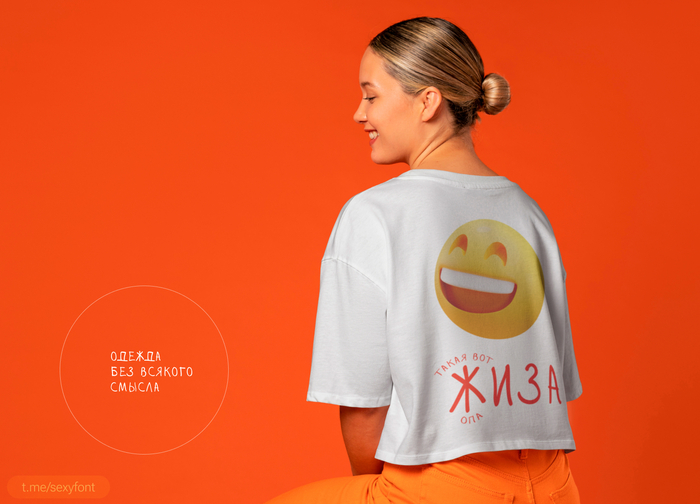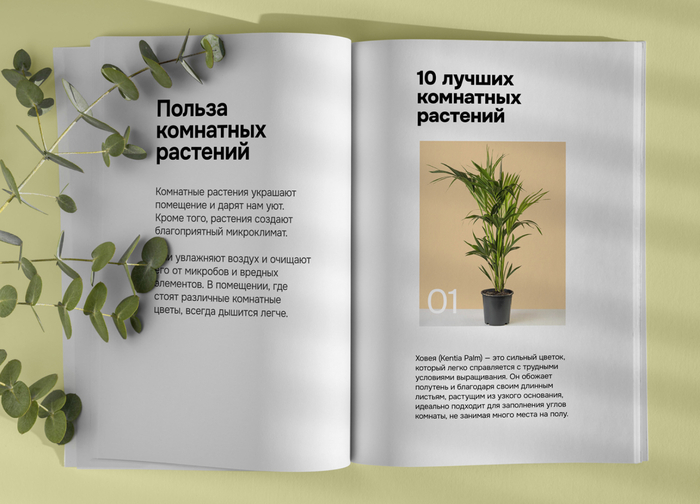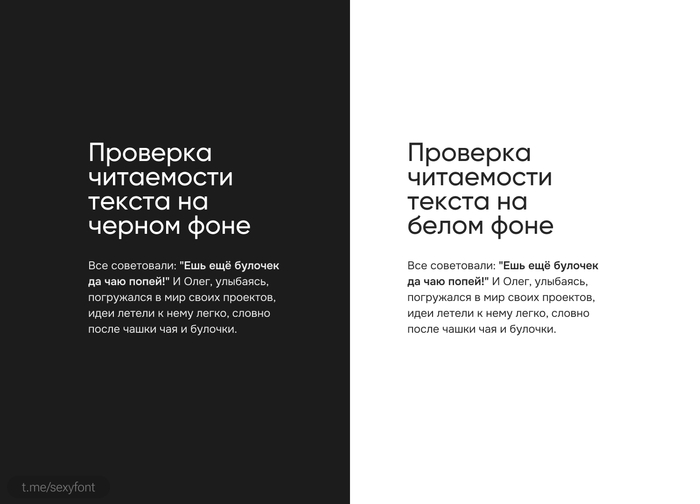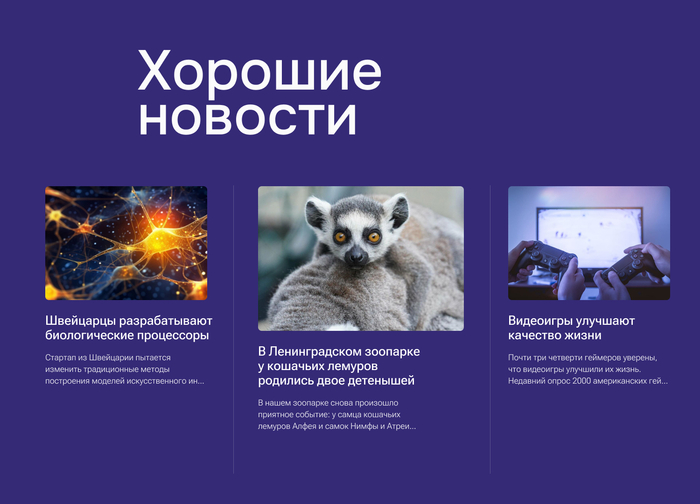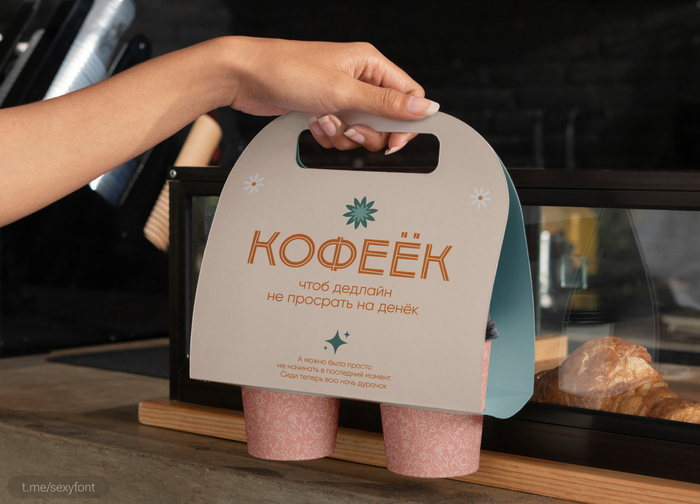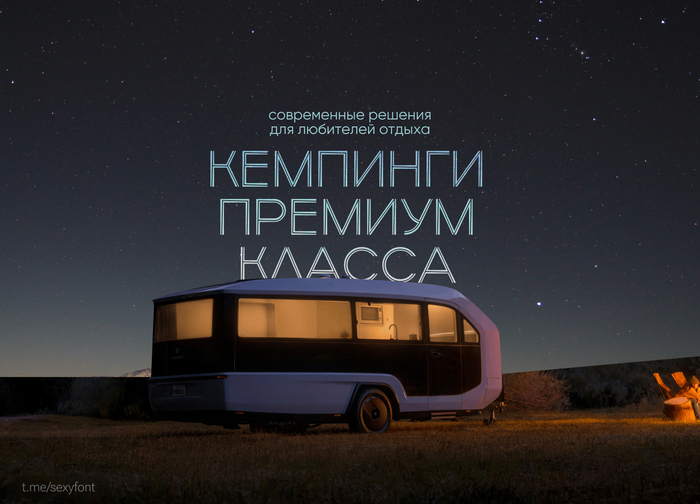
Занесенный. Снежный шрифт для новогодних проектов
Очень старенькая новогодняя классика) Думаю им еще дед мороз в 19 веке стихи писал. Но тем не менее решил сделать для него презентацию. Раньше этого никто не делал.
Operation napalm. Кириллица
Шрифт, сделанный в виде трафарета) Автор: GGBotNet. Бесплатно для личного и коммерции
Подборка бесплатных шрифтов
Йо! Рубрика: "цитаты Джейсона Стетхема" Ну или просто подборка серьёзных шрифтов.
–Miratrix
–Sports world
–St Simple Square
–Tablon
–Furore
Шрифт labor union. Бесплатная кириллица
Бесплатный шрифт с небольшими засечками. Вполне годная читабельность) Примеры использования показал в презентации.
Шрифт Zhizn
Изначально шрифт был разработан для одного из проектов благотворительного фонда «Жизнь», а впоследствии доработан и бесплатно распространяется по лицензии SIL Open Font License (OFL).
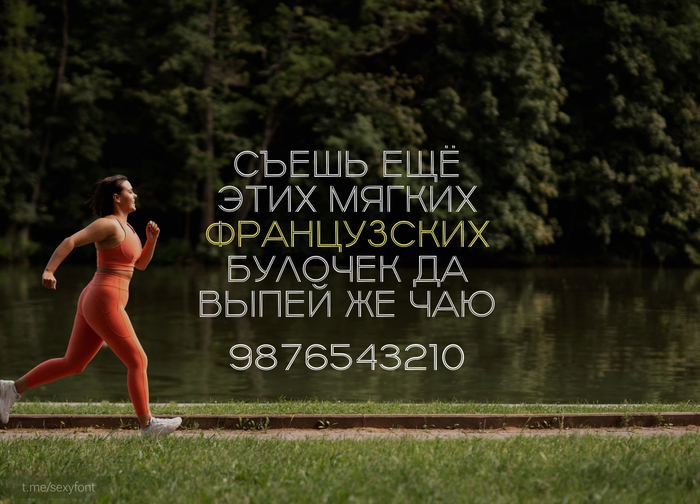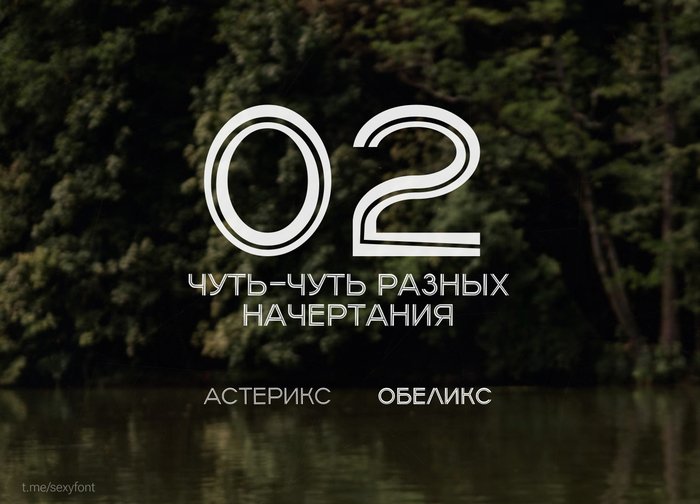
Onest. Свежий, читабельный шрифт с google fonts
Onest спроектирован как гибрид геометрического и гуманистического гротесков. Сочетает ёмкость и разборчивость, поэтому позволяет экономить пространство без потери читаемости.
Мне понравилась история разработки самого шрифта. Делался он год. С ней можно ознакомиться на оф. сайте
Шрифт Phorssa
Очень древний и необычный кириллический шрифт) Прям дикий. Но помню ситуацию мне такой и нужен был. Поэтому сохраняй куда-нибудь. Не сейчас, так позже. Автор: Juha Korhonen
Шрифт Capitellum. Кириллица
Capitellum. Необычный, бесплатный шрифт, естественно с кириллицей. Буквы сделаны в виде контурных линий. Есть даже 2 начертания, потоньше и чуть потолще)